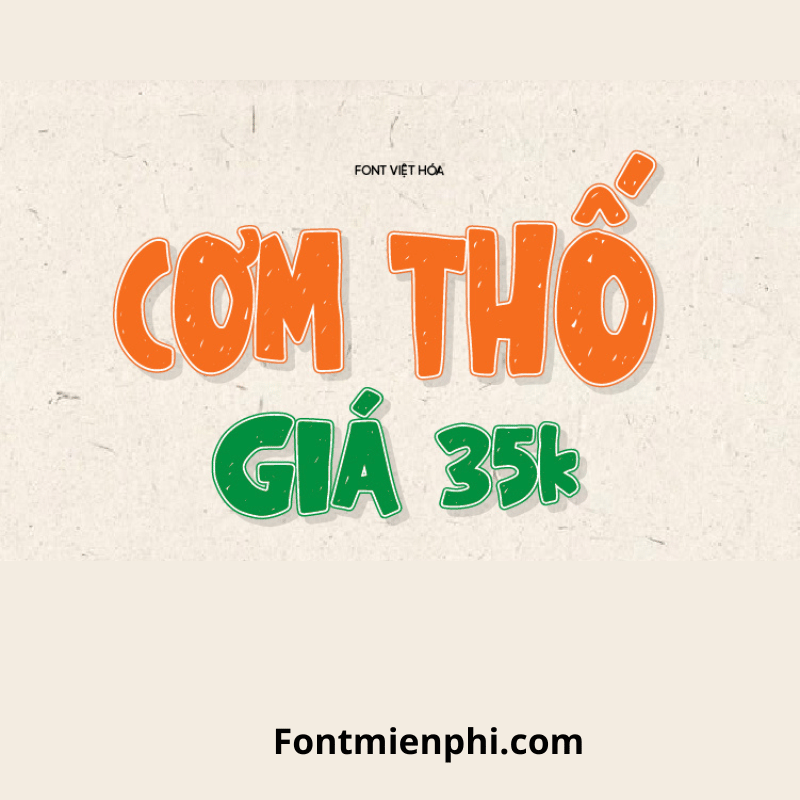
Font Việt hóa 1FTV VIP Sketchy in snow
Font Việt Hóa 1FTV VIP Sketchy in Snow – Nét Chữ Độc Đáo, Sáng Tạo
Font Việt hóa 1FTV VIP Sketchy in Snow là bộ font chữ nghệ thuật độc đáo, được thiết kế với phong cách phác thảo (sketchy) kết hợp hiệu ứng tuyết phủ (snow), mang đến vẻ đẹp tinh tế và sáng tạo. Font hỗ trợ đầy đủ tiếng Việt, phù hợp cho thiết kế đồ họa, poster, bìa sách, logo, và các dự án nghệ thuật khác.
• Phong cách Sketchy độc đáo: Nét chữ phác thảo tay, tạo cảm giác nghệ thuật và cá tính.
• Hiệu ứng Snow tinh tế: Điểm nhấn tuyết phủ giúp font chữ trở nên sống động, phù hợp với chủ đề mùa đông hoặc thiết kế sáng tạo.
• Hỗ trợ tiếng Việt: Đầy đủ dấu, tương thích với mọi phần mềm thiết kế.
• Đa dạng ứng dụng: Dùng cho in ấn, quảng cáo, social media, và các ấn phẩm nghệ thuật.
Font Việt hóa 1FTV VIP Sketchy in Snow là lựa chọn hoàn hảo cho những ai yêu thích sự sáng tạo và phong cách độc đáo. Với nét chữ phá cách và hiệu ứng tuyết ấn tượng, font chữ này chắc chắn sẽ làm nổi bật mọi thiết kế của bạn. Tải ngay để khám phá vẻ đẹp khác biệt!